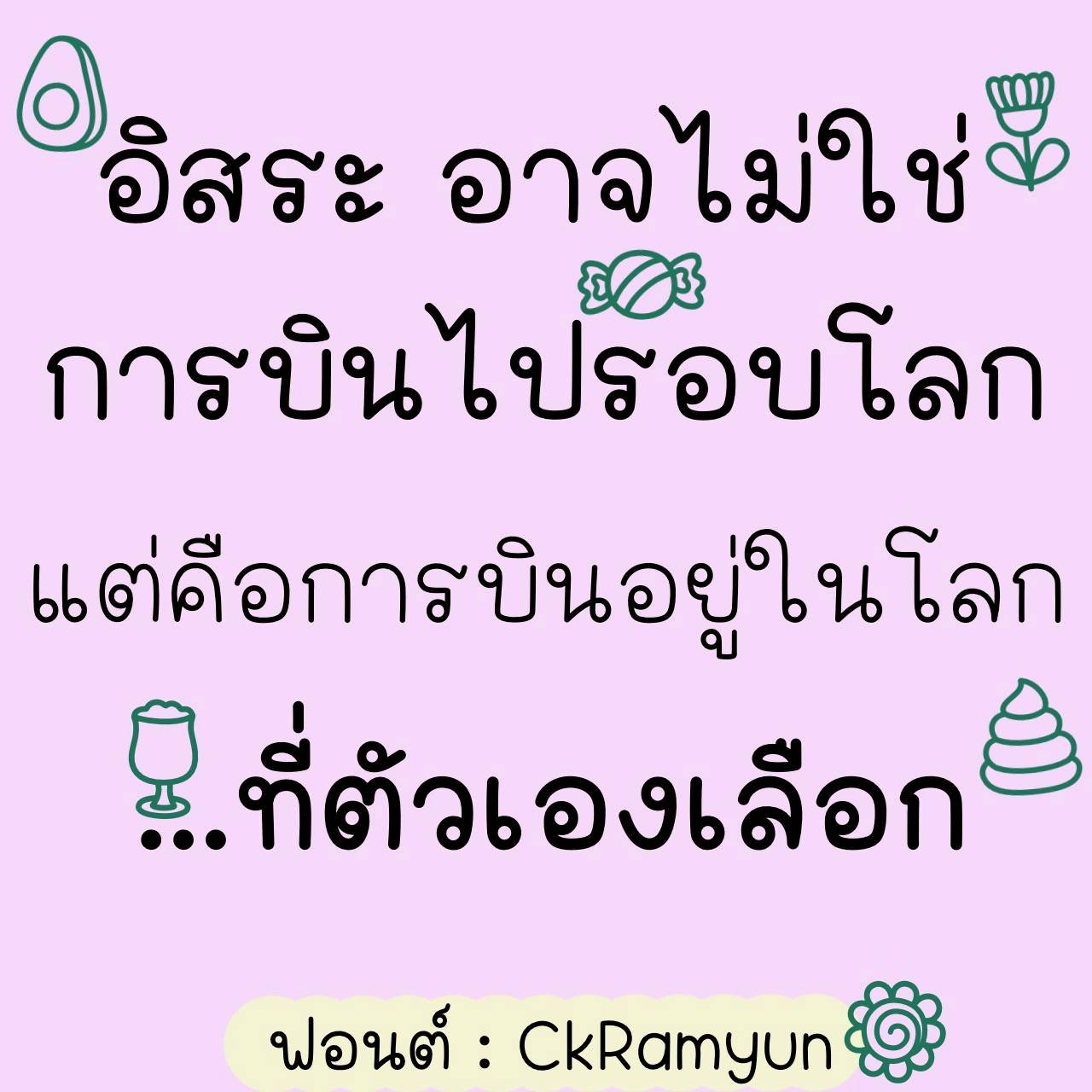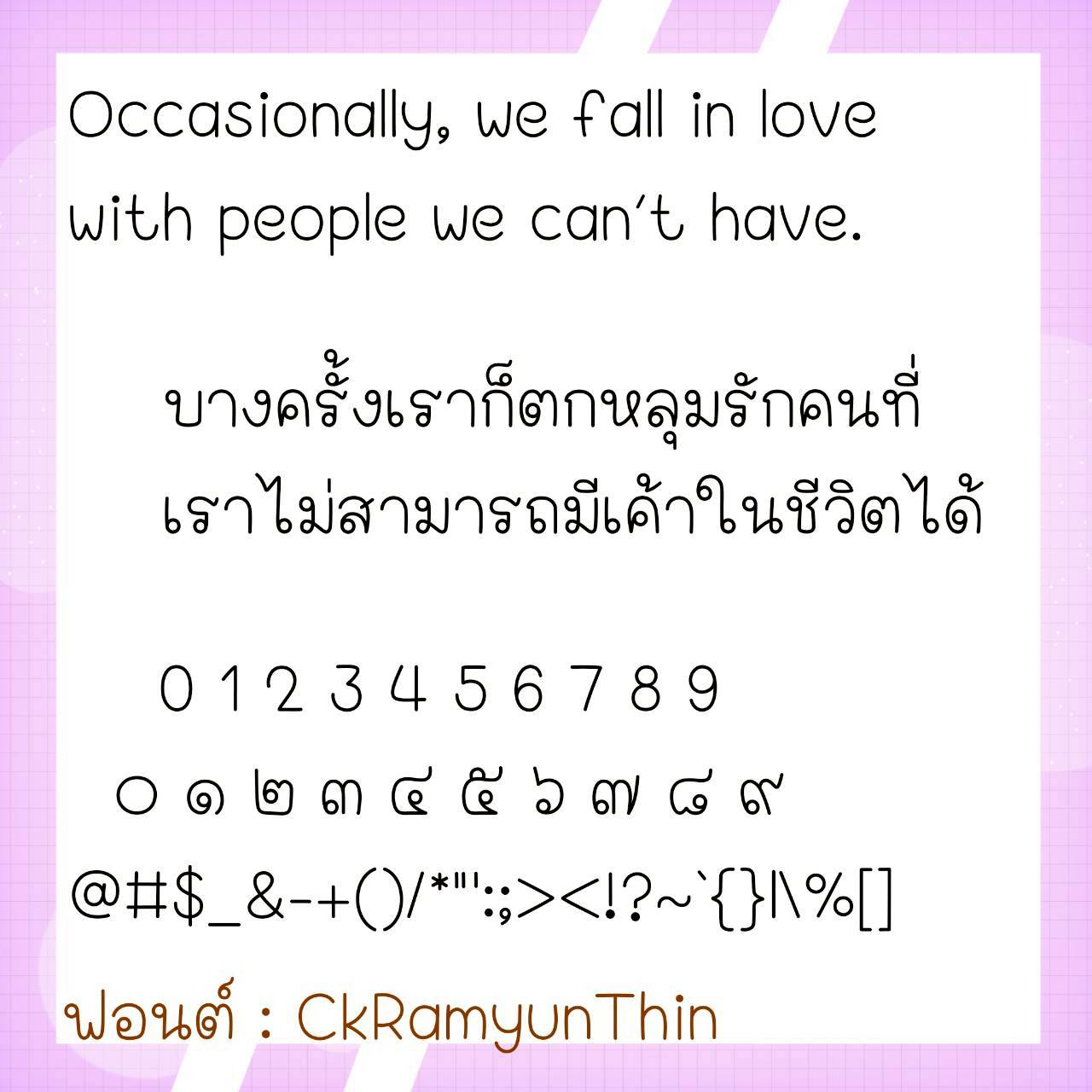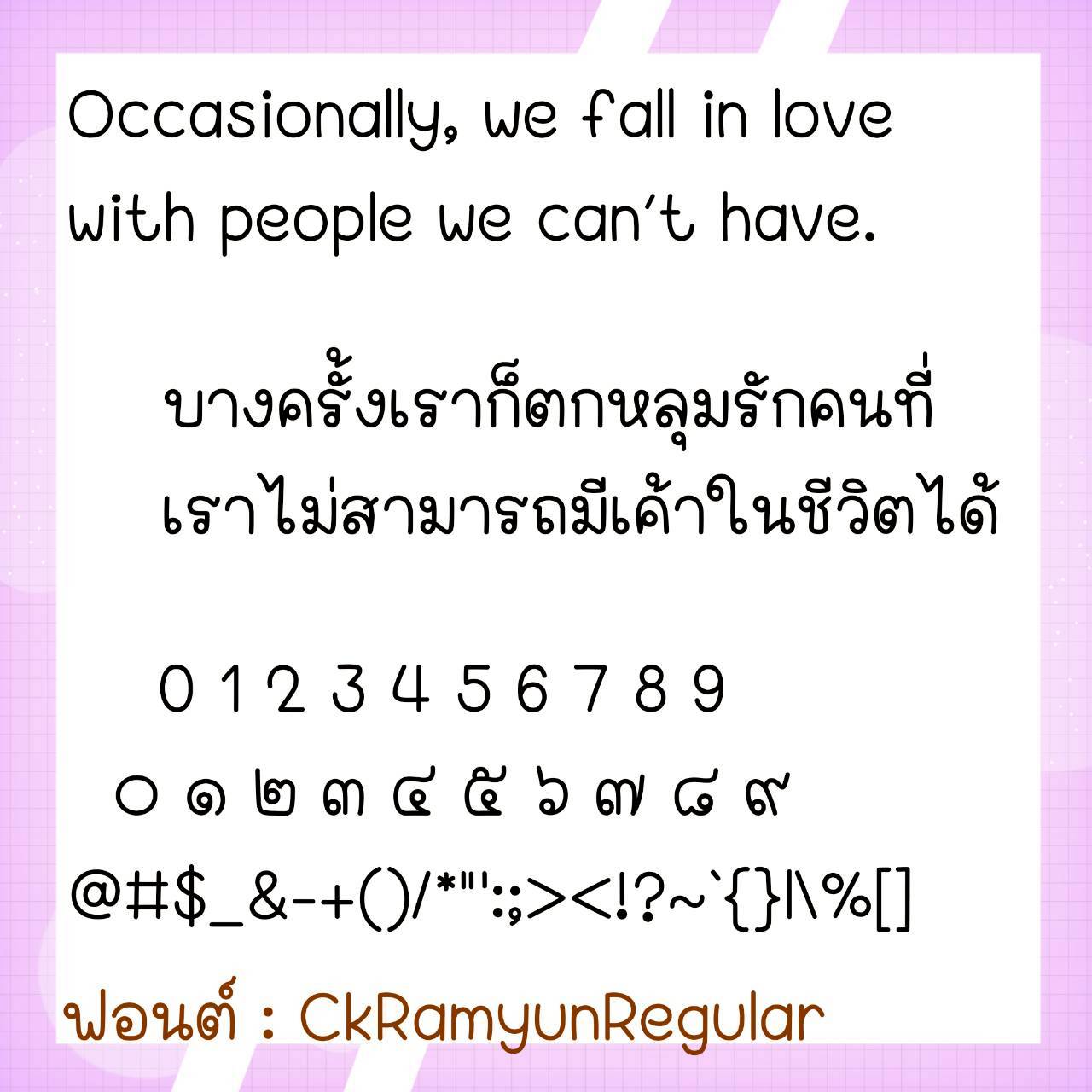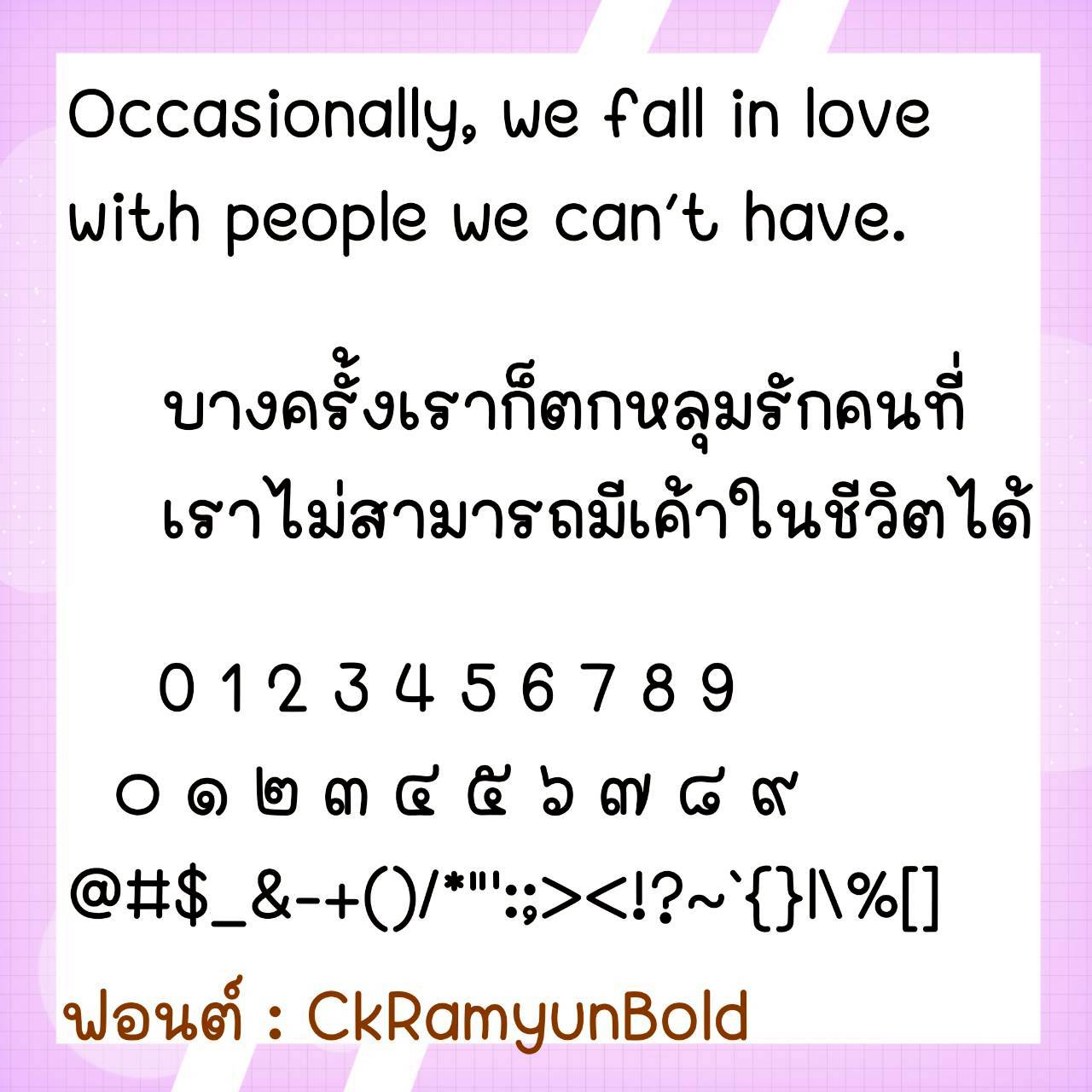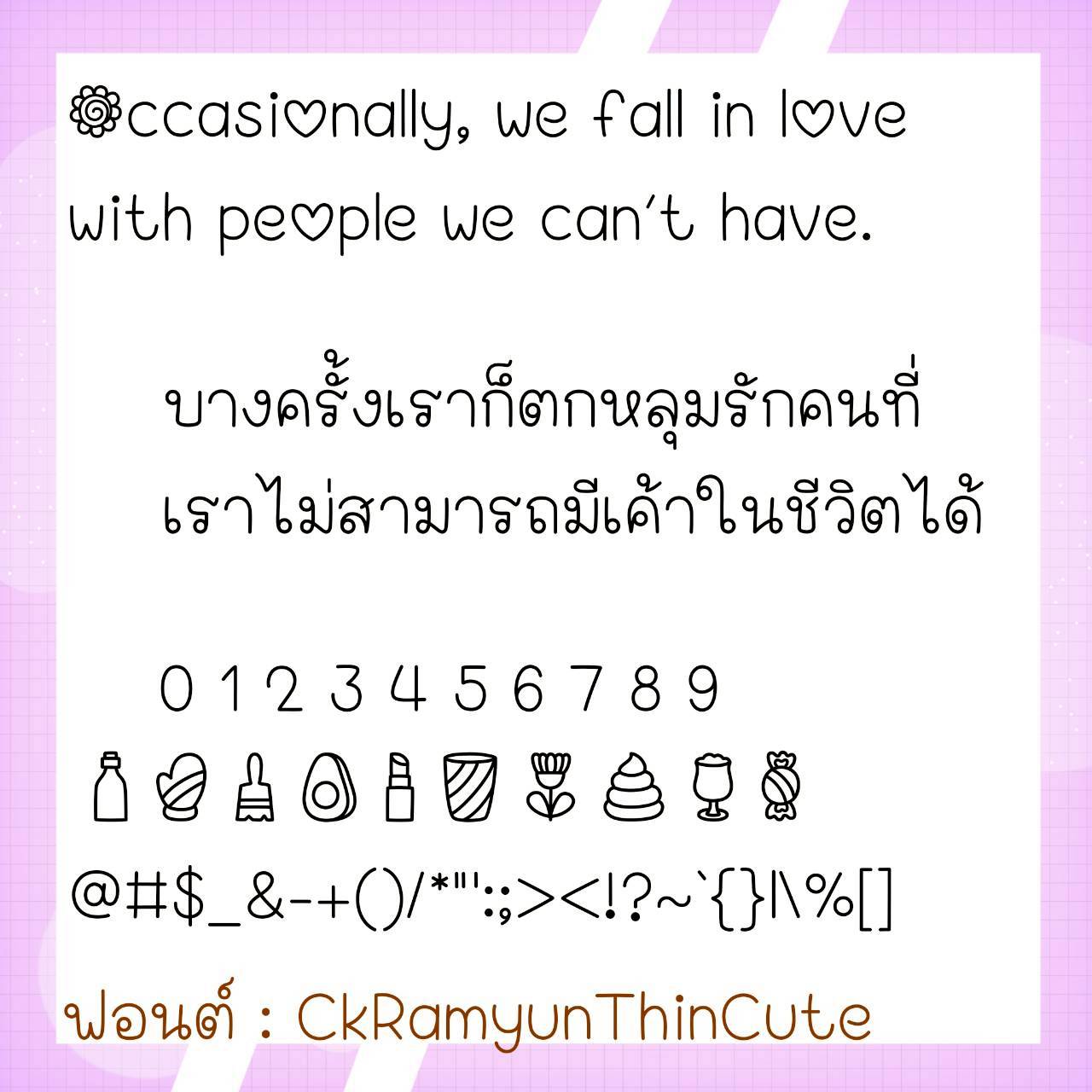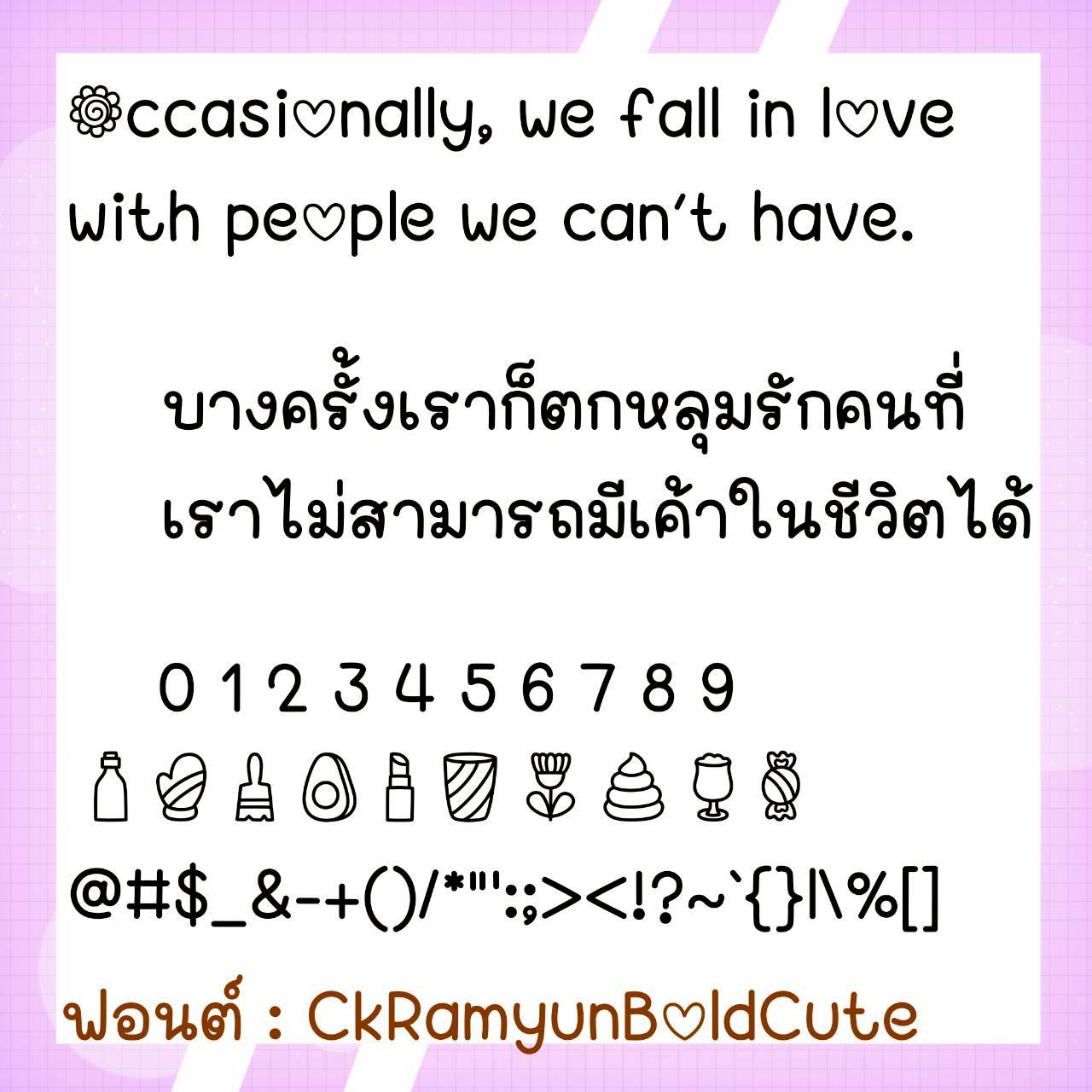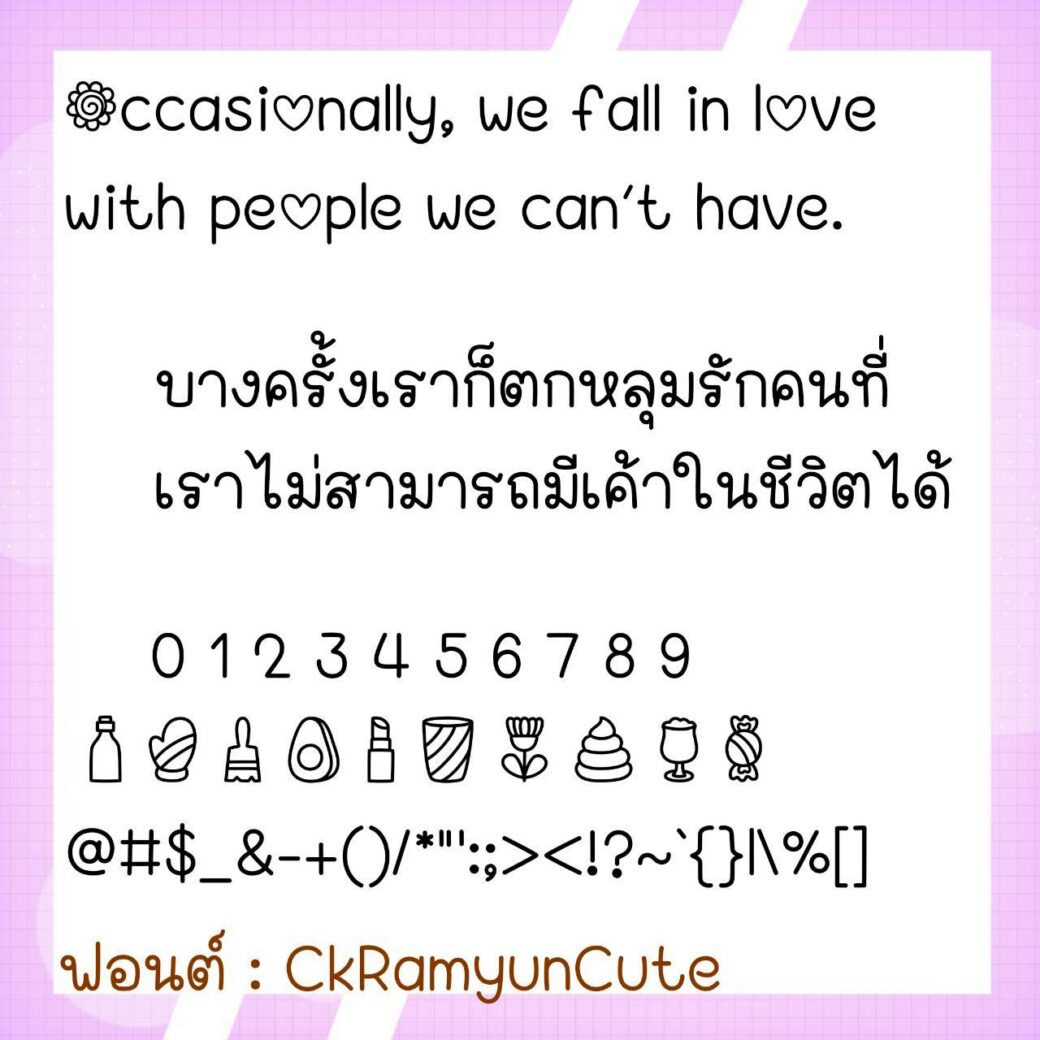
Font CkRamyun
ชื่อสินค้า : Font CkRamyun 💙
🔸 ฟอนต์ลายมือแนวตัวอ้วนกลมปุ๊กปิ๊ก เน้นอ้วนอ่านง่ายสบายตา มีความน่ารักในตัว และยังมีไฟล์อิโมจิน่ารักๆ ที่ใช้แทนเลขไทยให้ด้วยค่ะ 🥰💙
🔹 A handwritten font with a chubby, cute style. It emphasizes chubbyness, is easy to read, and is pleasing to the eyes. It has a cute character and also has a file of cute emojis that can be used in place of Thai numerals. 🥰💙